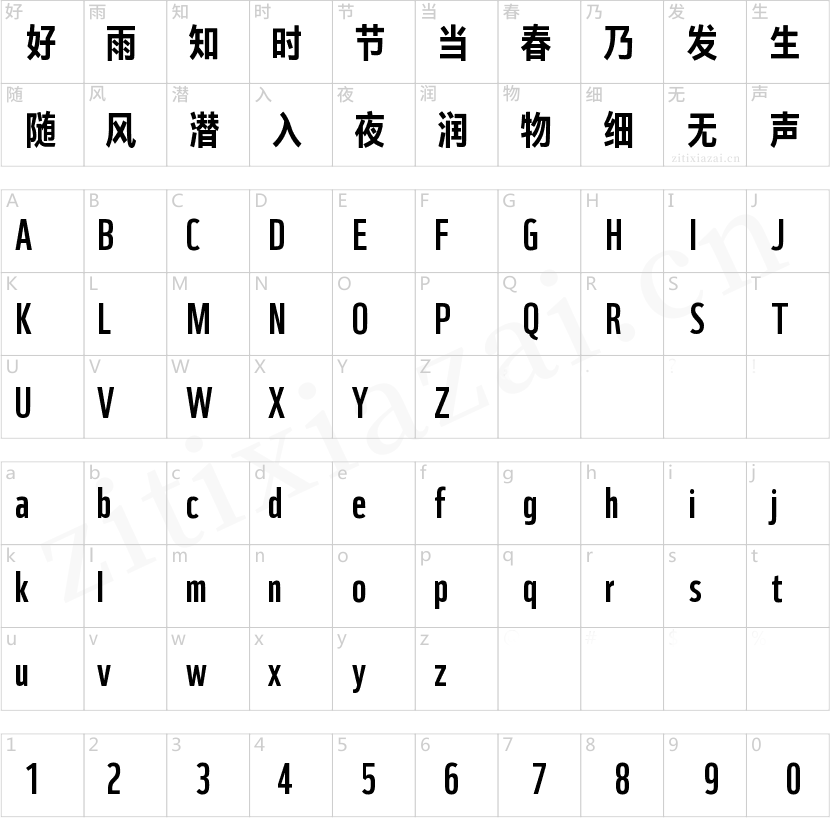
Aa星球黑
Aa星球黑,这款字体结构工整、笔画清晰,兼顾美观与易读性,适用于标题、正文、海报、包装、LOGO 等多种场景。字形优雅稳定,风格百搭耐看,适配日常排版与创意设计,让文字呈现更舒适、更具质感。Aa星球黑一笔一画,皆是细节,以均衡的比例、流畅的线条打造舒适视觉体验,字形端正大气,风格简约现代。无论是商业设计、品牌宣传还是日常排版,都能轻松驾驭,让文字更有格调与力量。Aa星球黑字体下载。